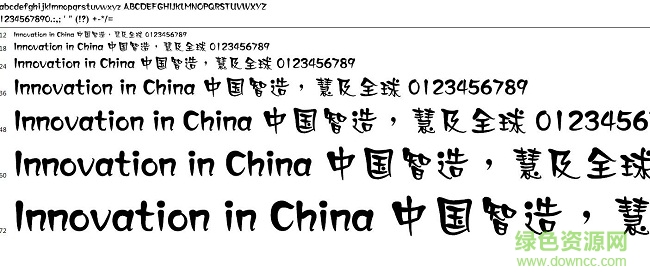
經典簡廣告字體是一款非常有個性的廣告字體,線條隨意,筆法豐富,風格新穎,上面粗下面細,用在廣告設計方面可以給人留下較深的印象,有需要者快來下載吧!
廣告字體就是根據商品的某些特點進而變化產生出來的一種字體,與看到字體的人達到共識,吸引眼球。
最早的漢字是商朝出土的甲骨文,到秦朝的大篆、小篆,秦時又出現了隸書,漸漸出現了草、狂草和楷書。字是出于象形分為甲骨文、金文、大篆、小篆、隸書、草書、行書、楷書,而后又有專家改為簡體字。